日常生活中有些场合上我们需要提笔写字,不过总是使用电脑打字的自己,提笔忘字或者是写的字七扭八歪是很常见的事情了,使用手机或者是电脑很方便,通过打字给对方传递信息。而往往导致我们出现这个情况了,能写得一手好字其实蛮加分的,会给其他人留下不错的印象。今天呢,咱们来说说字体被选入字体库的明星,看看他们写的字体如何。
首先这位是毛不易,毛不易在唱歌方面很优秀,参加选秀比赛时就很出彩了,歌曲曲调很容易被大家记住,有些歌曲则是很具有情感,能够打动人心。毛不易早期是一名护士,当时他就挺喜欢唱歌的。除了唱歌好听之外,毛不易写得一手好字,字体很潇洒,十分漂亮的字体。
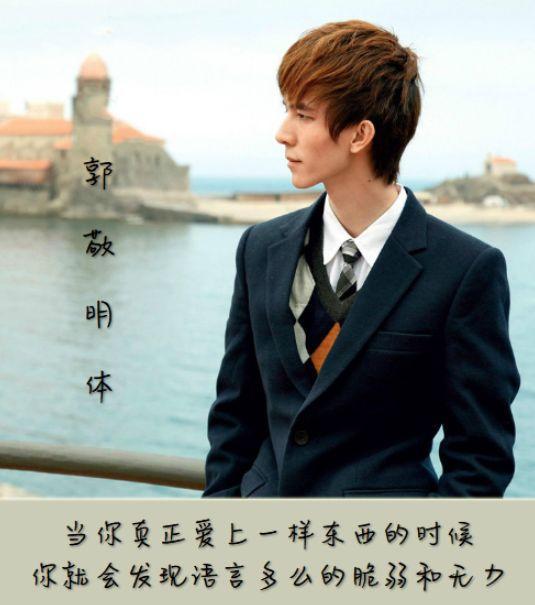
郭敬明是作家,导演。在最近热播的综艺节目《演员请就位》中担任评委,说话方式很有内涵,可以将自己的意思充分表达出来,让大家信服。郭敬明的文笔是很好的,自然口才也是了得,他的字也十分有特点,不是连笔字,也不是方方正正的字体,字体看着很柔和,没有太多的棱角。
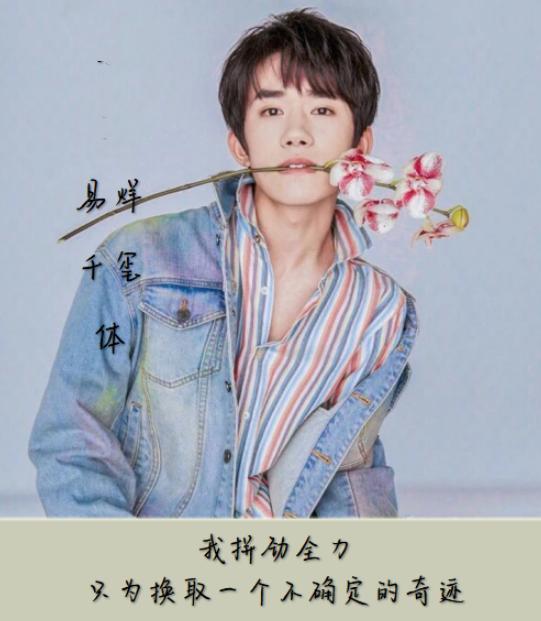
易烊千玺是TFBOYS组合中的成员,从小就多才多艺,妈妈对于他的培养很注重,参加选秀,拍广告,参加各种培训班等等。不过这些也都成为了千玺很宝贵的经历,唱跳样样精通,会变魔术,会川剧变脸,性格很开朗。千玺的字写得很好,曾经学习过书法。字迹干净,不缺少力量之外,还看着并不是很硬板。
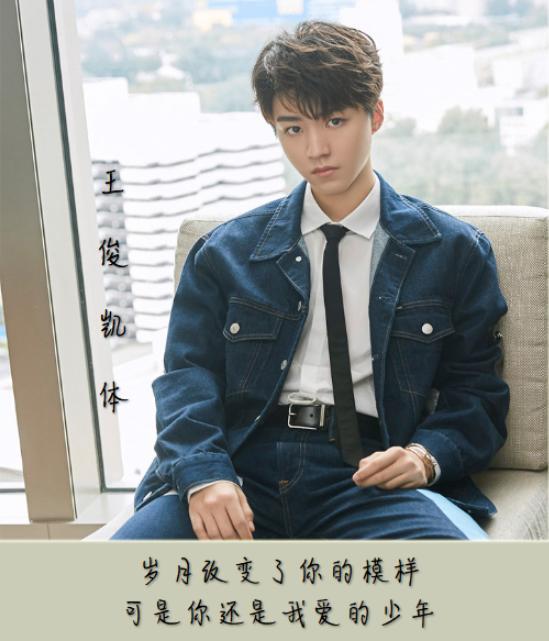
王俊凯与千玺是同一个组合的成员,并且是担任着队长的职务。小凯有种暖男感,出道后通过在娱乐圈中的磨练,各方面也都得到了很好的提升。看到他的字体,比较简约风,看着很自然,看到看出每一笔都喜欢有些拉长,尤其是捺的部分,形成了自己的写字风格。
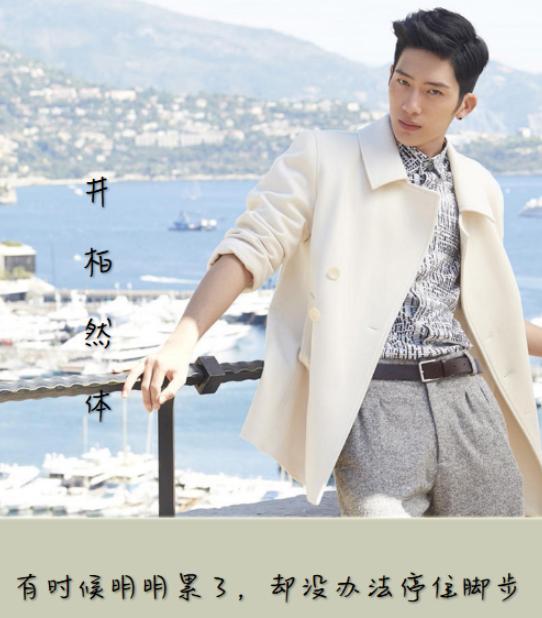
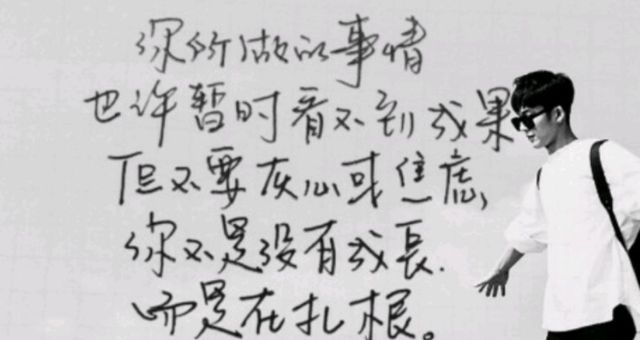
井柏然参加选秀节目出道,之后参演了《微微一笑很倾城》等等影视作品,除了唱歌与演技都很有实力之外,井柏然写的字也备受大家的喜欢,后来还被收入字库呢。井柏然的字并不像通常情况下大多人练习的楷体或者是隶属一样,而是一种独树一帜的艺术字,这个比起刻板的字体更显显现出一种内在的清新气息。